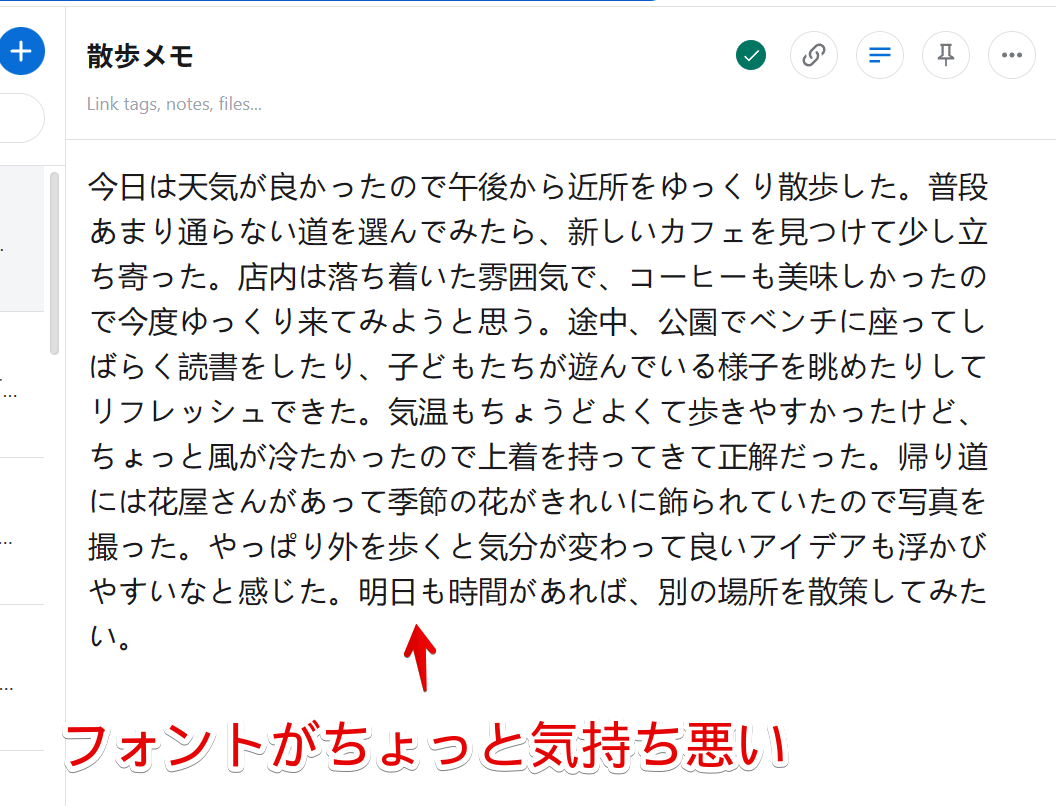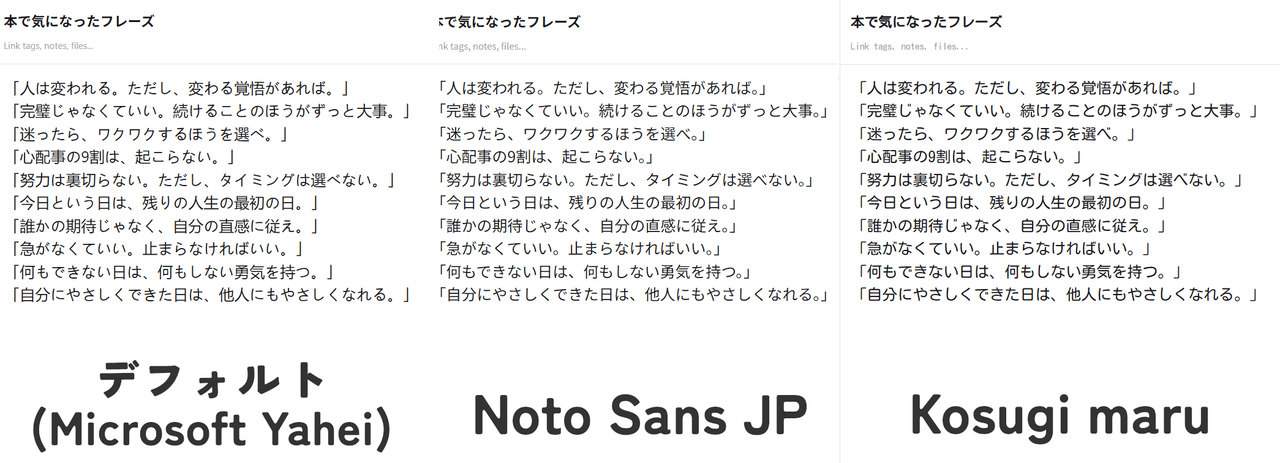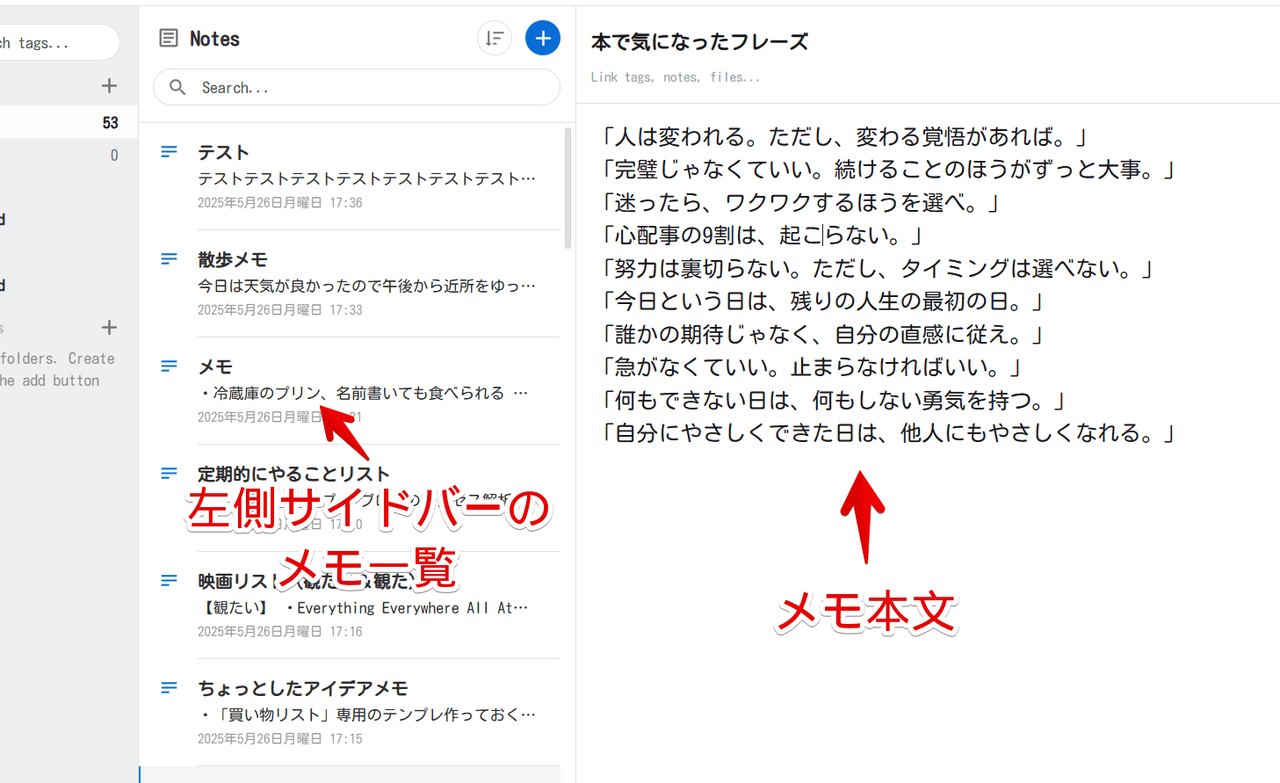
【Standard Notes】フォントを変更するCSS
この記事では、PCブラウザ版「Standard Notes」のタイトルやメモ本文のフォントを変更するCSSを書きます。
【Standard Notes】フォントを変更するCSS
僕はこれまで使っていた「Simplenote」から「Standard Notes」に移行しました。
二要素認証(2FA)やエンドツーエンド暗号化(E2EE)に対応していて、すぐにメモして複数デバイスで共有するという使い勝手も「Simplenote」と同じで最高です。
しかし、一点明らかな「うっ」ポイントがありました。フォントです。
パッと見、自分でも何でそう思うのか理由は分かりませんが、どことなく中国語っぽい雰囲気がするフォントでした。
PCブラウザ版「Standard Notes」のフォントが「Microsoft Yahei」で汚い画像
実際開発者ツールを見てみると、「Microsoft Yahei(微软雅黑体)」というフォントが使われていて、調べてみるとWindowsに標準インストールされている簡体字中国語フォントらしいです。
だからどことなく中国語っぽい雰囲気がするのかーと納得です。
軽く調べた感じ、無料版の「Plain Text」だとフォントを変更するようなオプションが見当たりませんでした。
もしかしたら有料版にして「Super」ノートを使えば変えられるかもしれません。僕は今のところ有料版にする気はないため、CSSで自身の環境上だけで変更してみます。
自身の環境上のみで他人には一切影響しません。
「Standard Notes」のフォントを変更するCSS
CSSを書き込む
以下のコードを書き込みます。
CSS
/*左側サイドバー(一覧)のフォント*/
html, body {
font-family: "Kosugi maru";
}
/*メモ本文のフォント*/
.font-editor {
font-family: "Kosugi maru";
}
font-family」を皆さん好きなフォント名に書き換えます。フォント名の書き方は各自調べてみてください。
PCにインストールされているフォントじゃないとダメなので、自分のOSに何のフォントがインストールされているか先に把握して、そのフォントをCSS指定するためにはどういう正式名称を書けばいいか調べます。
上記はWindowsに標準インストールされている「Noto Sans JP」、Macに標準インストールされているらしい「Hiragino Kaku Gothic ProN」を両方指定しているので、こだわりがない場合は上記のままでもいいと思います。
Macに関しては僕は持っていないのであくまで情報をもとに書いているだけです。実際反映されるかは不明です。
フォントが変わったか確認
指定したフォントになります。メモ本文と左側サイドバーのメモ一覧(リスト)で別々のフォントを指定できます。
PCブラウザ版「Standard Notes」のフォントをCSSで「Kosugi maru」に変更した画像
僕は角丸フォントが好きなので、「Kosugi Maru」というのをWindowsにインストールして、以下のように指定しています。
CSS
/*左側サイドバー(一覧)のフォント*/
html, body {
font-family: "Kosugi maru";
}
/*メモ本文のフォント*/
.font-editor {
font-family: "Kosugi maru";
}
デフォルト、Noto Sans JP、Kosugi Maruにした比較画像を貼っておきます。
PCブラウザ版「Standard Notes」のフォントを変更した比較画像
感想
以上、PCブラウザ版「Standard Notes」のタイトルやメモ本文のフォントを変更するCSSでした。
唯一PCブラウザ版を使っていてちょっと嫌だな。マイナスだな。と思った点だったので、CSSという若干手間がかかる作業とはいえ好きなように変更できて良かったです。
Androidスマホアプリ版はCSSが使えませんが、そもそもアプリ版はブラウザ版と違ってOS側の規定フォントが採用されるのか、特に汚くなかったので気にしていません。
Androidスマホアプリ版「Standard Notes」のフォント画像
PCブラウザ版も、最初はブラウザの規定フォントが採用されるのかなと思い設定変更してみましたが、変わりませんでした。
Windows版「Google Chrome」ブラウザのフォント設定画像